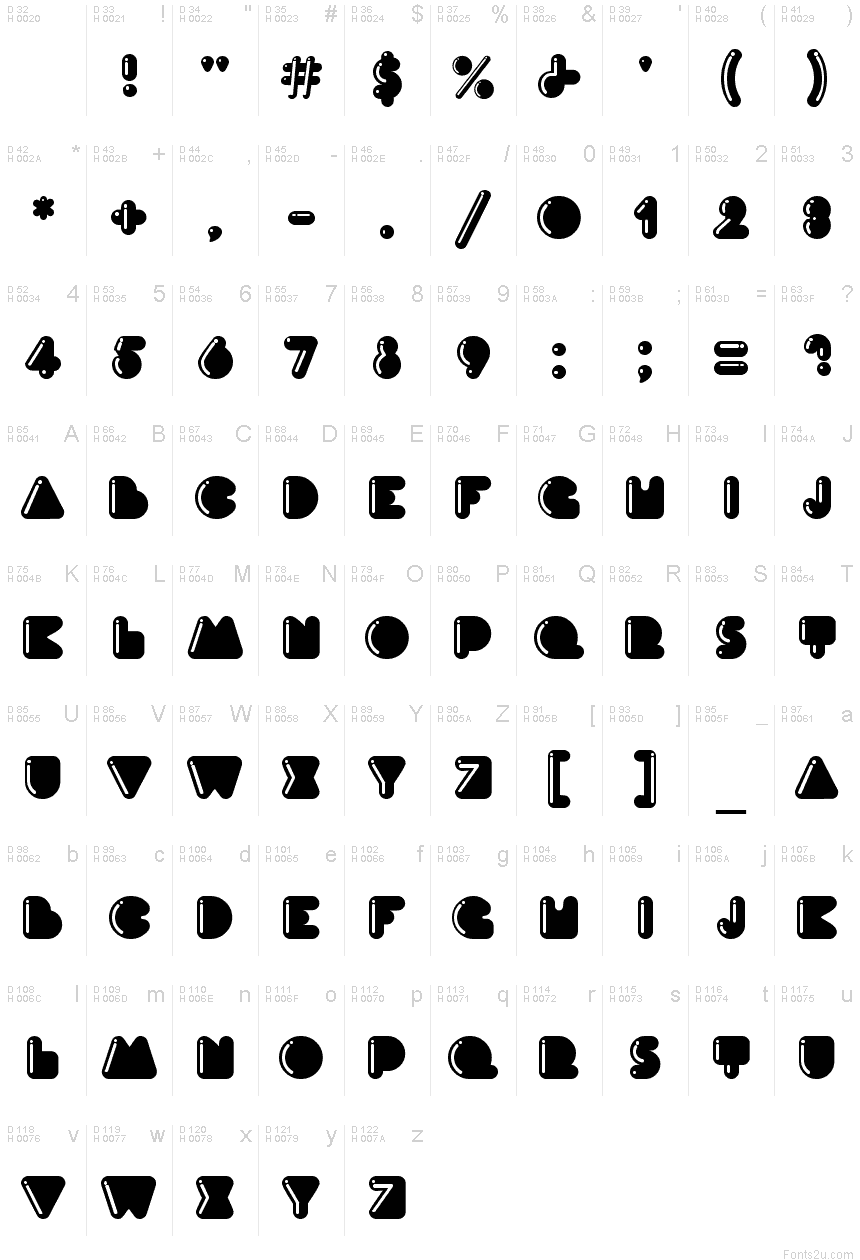
Mindy to darmowy, groovowy krój displayowy z bąbelkowym klimatem lat 70. i sylwetką przypominającą lampę lawę. Litery są szerokie i ciężkie, zbudowane z dużych, zaokrąglonych form z subtelnymi wewnętrznymi akcentami, które nadają fontowi zabawny, napuchnięty rytm, daleki od surowej geometrii.
Świetnie sprawdzi się na plakatach muzycznych, w brandingu kawiarni w stylu retro, na ulotkach imprezowych, opakowaniach dla młodzieży i śmiałych nagłówkach w mediach społecznościowych, gdzie przyjazny, nostalgiczny klimat liczy się bardziej niż formalność. Jako darmowy font, Mindy dobrze wygląda także w krótkich tekstach na okładkach, planszach tytułowych i logotypach, ponieważ te pulchne krzywizny i drobne akcenty sprawiają, że nawet krótkie słowa wyglądają żywo.